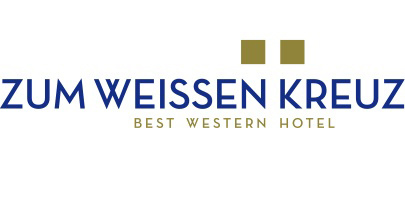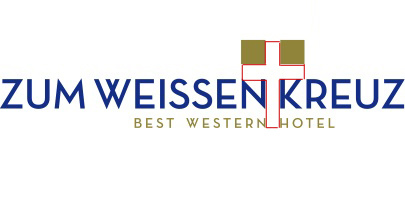
Schrift für erstklassiges Hotel
Deutsch und englisch gemischt („BEST WESTERN HOTEL“ und „WEISSES KREUZ“): Muß das sein?
Zum roten Hintergrund des weißen Kreuzes: Das Schweizerkreuz ist weiß auf rot abgebildet. Der Begriff „western“ erweckt in mir die Vorstellung nach etwas „erdigem“, ockerfarbenem.
Zur Farbe des Schriftzugs „WEISSES KREUZ“: Muß er rot sein?
Zum weißen Hintergrund der gesamten Darstellung: Nicht nur eine Frage des Kontrastes, welcher in sämtlichen oben gezeigten Beispielen extrem ist, sondern auch eine Frage des Darzustellenden.
Zur Schriftwahl: Wäre meiner Meinung nach gründlich zu überdenken.
Zur Form des Kreuzes: Diese ebenfalls.
Deutsch und englisch gemischt („BEST WESTERN HOTEL“ und „WEISSES KREUZ“): Muß das sein?
Ja, muss.
Best Western ist die Hotelkette, die heißt nun mal weltweit so*.
Weißes Kreuz ist das Hotel, das in Österreich steht, somit deutsch.
Beides nicht zu ändern.
* natürlich könnte man bei Best Western anrufen und sie fragen ob sie ihren Markennamen nicht an das jeweilige Land lokalisieren möchten. Ich glaube die Antwort würde »nein« lauten.
… sieht alles irgendwie nach samariter, evangelisches gemeindezentrum oder krankenhaus aus.
markus, ich denke du weisst was ich damit sagen will. es ist nicht meine aufgabe hier irgendwelche buchstabenabstände, gestaltungsraster etc. aufzuzählen, dazu fehlt mir einfach die zeit und außerdem ist es DEIN job dies zu erkennen. ich kann dir gern sagen was ich mit dem logo in verbindung bringe und das ist eben nicht ein hotel der extraklasse.
georgs favorit gefällt mir z. b. überhaupt nicht. das ist natürlich alles meine meinung und hängt viel mit presönlichem geschmack zusammen. du weisst ja 5 designer, 6 meinungen.
ich mag die abgerundeten alternatezeichen der luxury nicht. das E sieht aus wie das eurozeichen. generell find ich die strichstärke des kreuzes zu fett.
am besten finde ich entwurf nr. 1, alles ruhig geglieder, keine spielereien. das kreuz sticht negativ hervor, gut gelöst. ggf. solltest du an dieser idee weiterarbeiten. die idee von sebastian mit dem versal-ß kam mir auch sofort, ich würde das mal testen wie es aussieht.
Ein Versal-ß würde ich auf keinen Fall verwenden. Schließlich soll ein Hotel international vermarktet werden. Und dabei einen Buchstaben zu verwenden, die der größte Teil der Erdenbürger nicht kennt, halte ich für äußerst ungeschickt. Schließlich geht es hier nicht um typografische Spielereien und Schönheitswettbewerbe, sondern schlicht und ergreifend um wirtschaftlichen Erfolg.
Deshalb auch mein Einwand, daß Best Western optisch nicht in Erscheinung tritt. Ob das bei Best Western zulässig ist, weiß ich nicht. Aber sinnvoll ist die Einbindung der Dachmarke auf alle Fälle. Es geht ja darum: „Ich war schon einmal in einem Best-Western-Hotel, und da hat es mir gut gefallen. Also wähle ich auch jetzt das Best-Western-Hotel, da bin ich mir der Qualität sicher.“
Aber wie gesagt, daß ist nur meine Meinung, ohne natürlich die Begleitumstände und die Kundenabsprachen zu kennen.
(Nur Spaß: Das wäre doch das ideale Beispiel, um die Akzeptanz eines Versal-ß auszutesten...)
Trotzdem schreibst Du „muss“, statt muß – wohl nur zum Spass? Und dies: „auszutesten…“ – warum auch immer.
Ein Versal-ß würde ich auf keinen Fall verwenden. Schließlich soll ein Hotel international vermarktet werden. Und dabei einen Buchstaben zu verwenden, die der größte Teil der Erdenbürger nicht kennt, halte ich für äußerst ungeschickt.
ok, stimmt.
wie sehen eigentlich die anderen logos der hotels aus? haben die auch welche? ich meine jetzt nicht das allgemeine best western logo. wobei man überlegen könnte ob man die farben des hauptlogos übernimmt. blau, gelb, rot.
Wenn ich so an mein nicht-grafisches Leben denke, in dem ich des öfteren in guten, sehr guten und noch besseren Hotels absteigen durfte (ohne selbst dafür bezahlen zu müssen :D ), und mir mal vor Augen führe, wie bei den "Leading Hotels" und anderen die Logo-Sprache ist, dann gefällt mir die Nummer 3 am besten. Zunächst ist das Kreuz im Signet nur auf den zweiten Blick ein "deutliches" Kreuz, durch das umgebende Karo und die angeschnittenen Kreuzarme wirkt es eher wie ein (in der gehobeneren Preisklasse) branchentypisches ungegenständliches Signet. Besser als hier wirst Du den Spagat wohl nicht hinbekommen. Die Schrift und Farbigkeit finde ich passend, Dezenz spricht die Zielgruppe hier am meisten an (Teure Servietten sind ja auch Weiß auf Weiß bestickt, und die Livree des Bell Captains wird auch immer schlichter, je besser das Hotel ist ...).
PS: Georgs Favorit (Nummer 2) ist mir ein Tick zu "familiär", zwar nicht gleich Garni, aber doch noch nicht ganz 4 Sterne.
Trotzdem schreibst Du „muss“, statt muß – wohl nur zum Spass? Und dies: „auszutesten…“ – warum auch immer.
Nein, ich werde mich nicht auf realitätsfremde Grabenkämpfe einlassen... nein nein nein...
Nur mal als Zusammenfassung:
- Die Überlegung, ein Versal-ß einzubringen, halte ich für unernst gemeint.
- "Best Western" ist eine Hotelkette von selbständigen Hotels mit einer Art "Bestpreis-Garantie". Keine Hotelkette mit völlig identischem äußeren Erscheinungsbild wie z.B. Holiday Inn, aber auch kein reines Franchising-Konzept. Jedes Hotel darf den Zusatz "Best Western" führen, es gibt -zig Best-Western-Kundenkarten, denen in all diesen Hotels ein durchgängig guter Service und gute Preise geboten werden. Auf den Zusatz "Best Western" zu verzichten, halte ich für absolut kontra-produktiv und wäre auch beim Auftraggeber mit Sicherheit nicht durchzusetzen.
›Die Nr. 3‹ die du ansprichst hätte mir auch am Besten behagt; ich denke, dass diese Lösung eigenständiger und unverwechselbarer gewesen wäre. ›Nr. 5‹ gefällt mir zwar sehr gut, aber ich bin mir sicher, dass es das so ähnlich da und dort schon gibt.
5 Gestalter, 10 Meinungen + ein paar revidierte sobald unter anderen Gesichtspunkten, Argumenten und Meinungen betrachtet... :)
Die gewählte Variante ist sicher keine schlechte Wahl.
Kann man überhaupt die optimale Lösung finden, die allen zusagt (Gestalter, Kunde, anderen Gestaltern, Kunden des Kunden)?